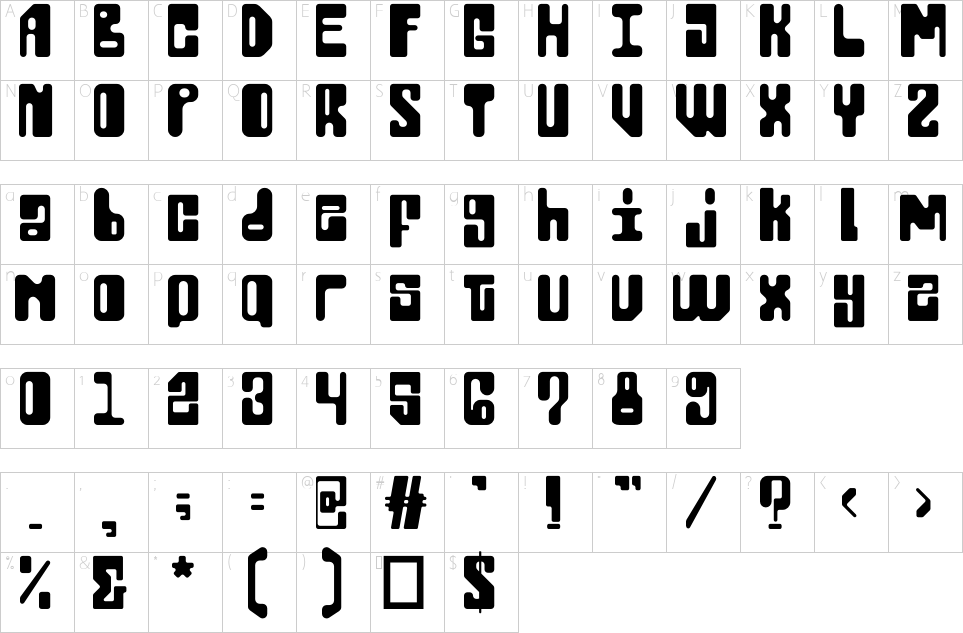
Descubra a Wofisty Font, uma opção gratuita e sofisticada para seu próximo projeto de design. Desenhada pelo talentoso Jada Akbal, essa fonte é perfeita para adicionar um toque único aos seus textos digitais. Com um design moderno e elegante que se adapta a qualquer plataforma – seja Windows ou Mac – ela é uma escolha óbvia para designers amadores e profissionais. Com mais de 1,087 downloads, é evidente que os usuários estão se beneficiando das suas qualidades visuais e facilidade de uso. Próxima vez que precisar de um design simples e impecável para o seu trabalho, considere a Wofisty Font. Seja em sua próxima página web, aplicativo ou projeto gráfico, ela certamente complementará sua criação com perfeição.